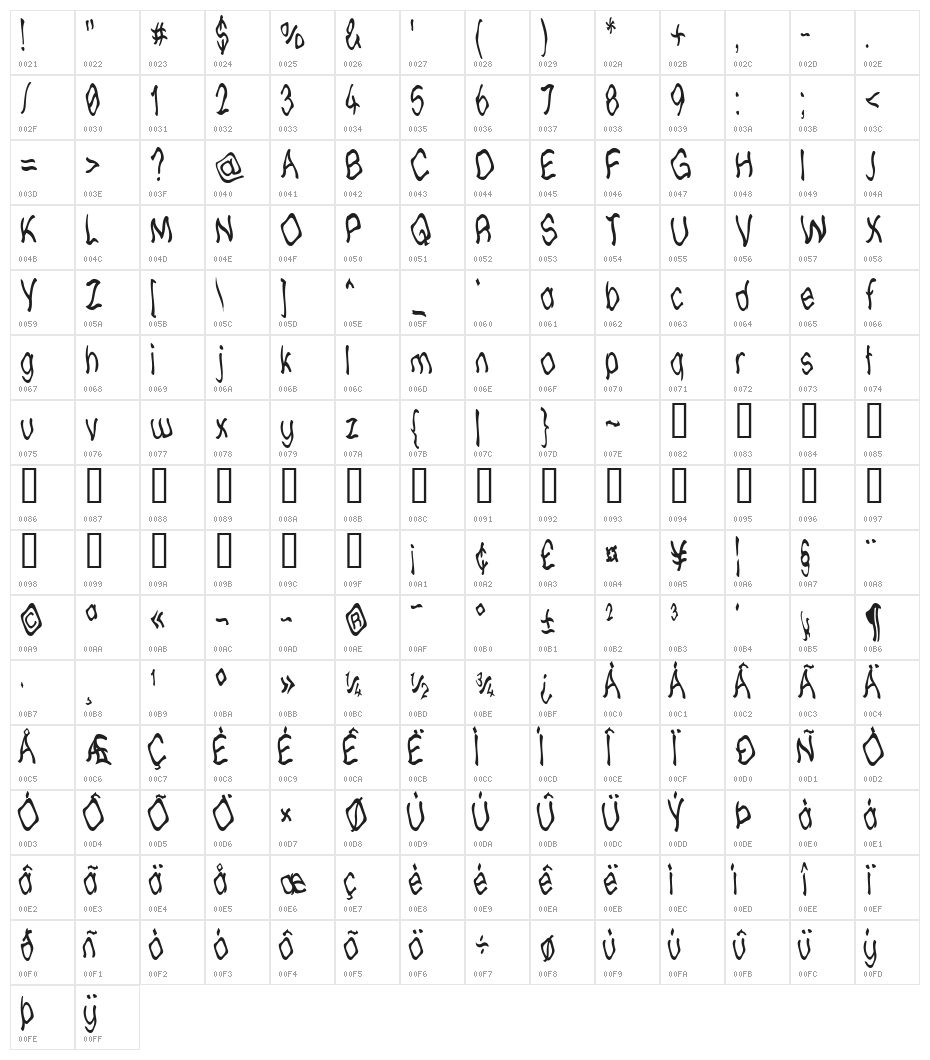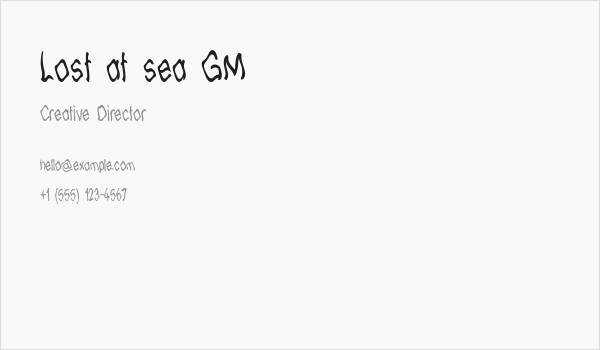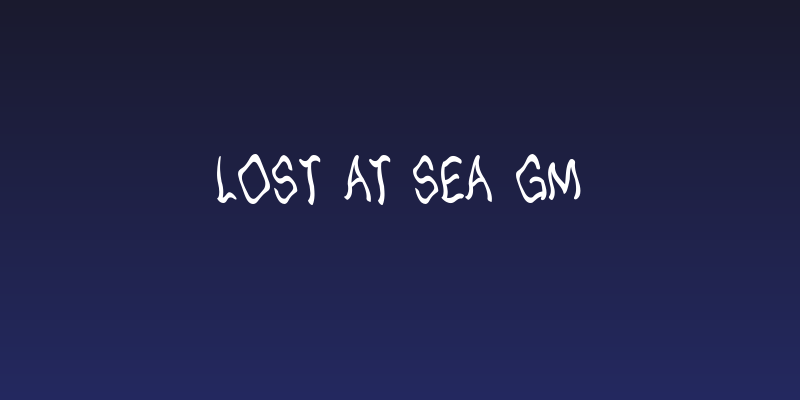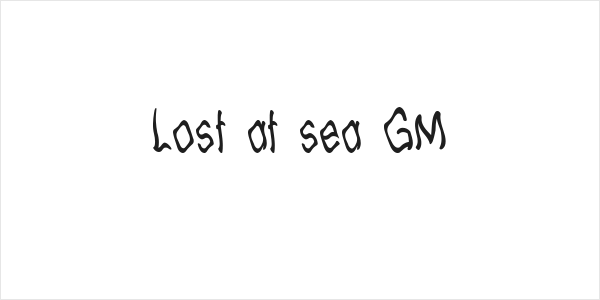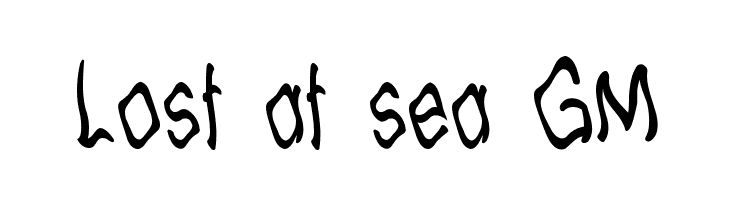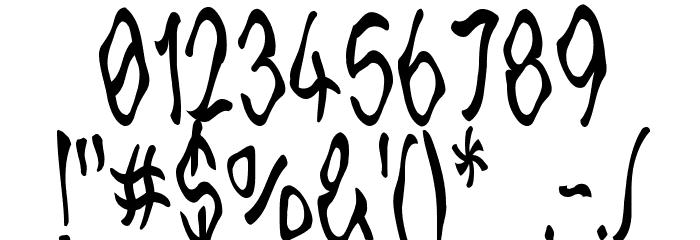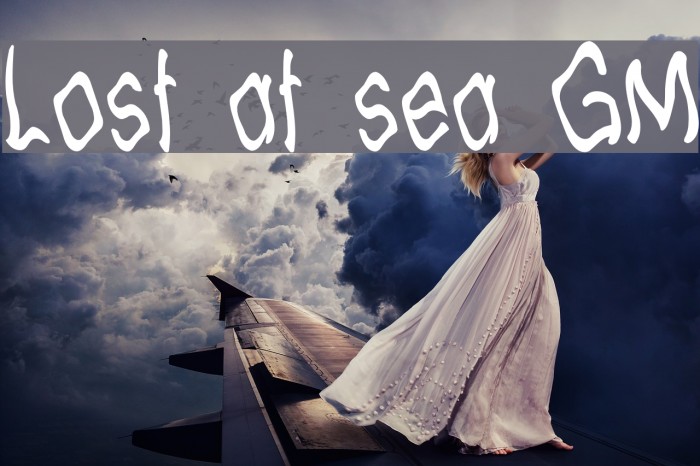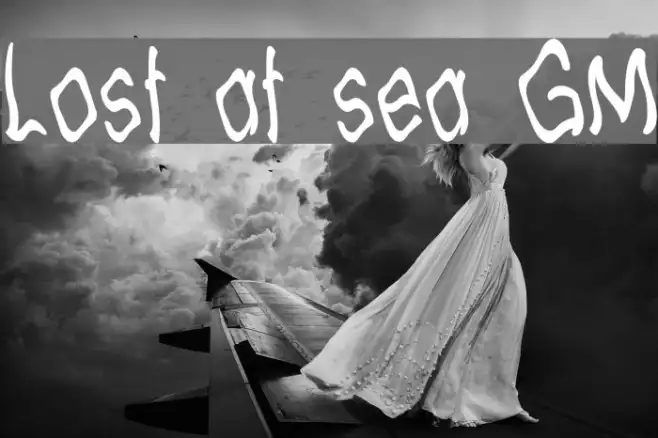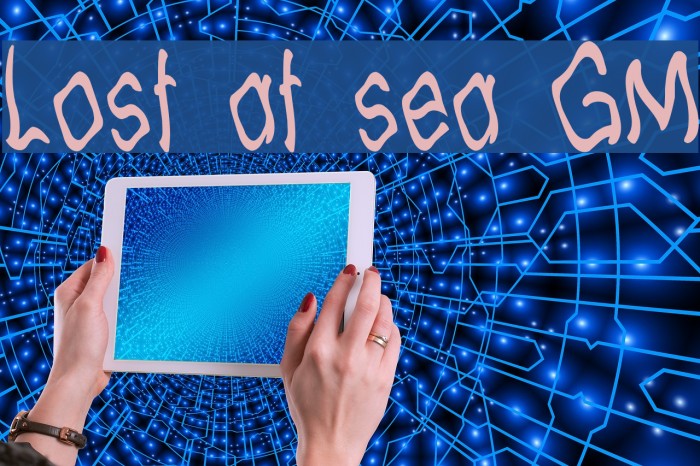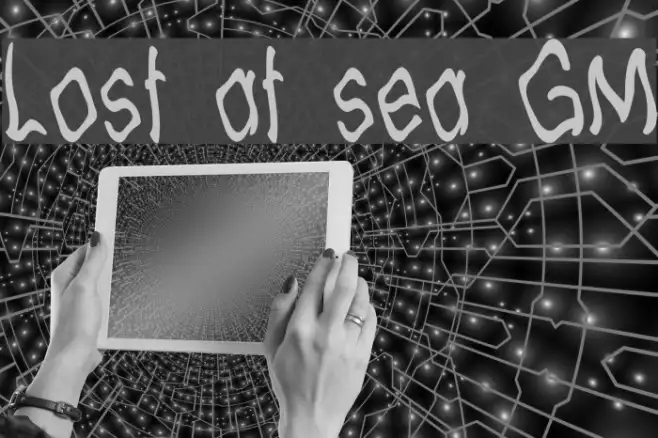
Lost at sea GM Font
Fonts by Graham Meade - GemFonts
| Cas d'utilisation | Headlines, Logos, Creative projects |
| Projets proposés | Great for children's books, creative posters, beach-themed events, and artistic branding. |
| Auteur | Fonts by Graham Meade - GemFonts |